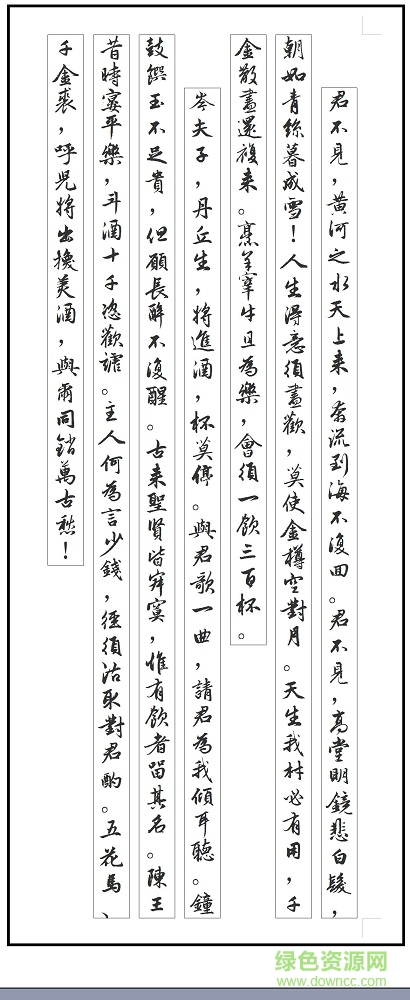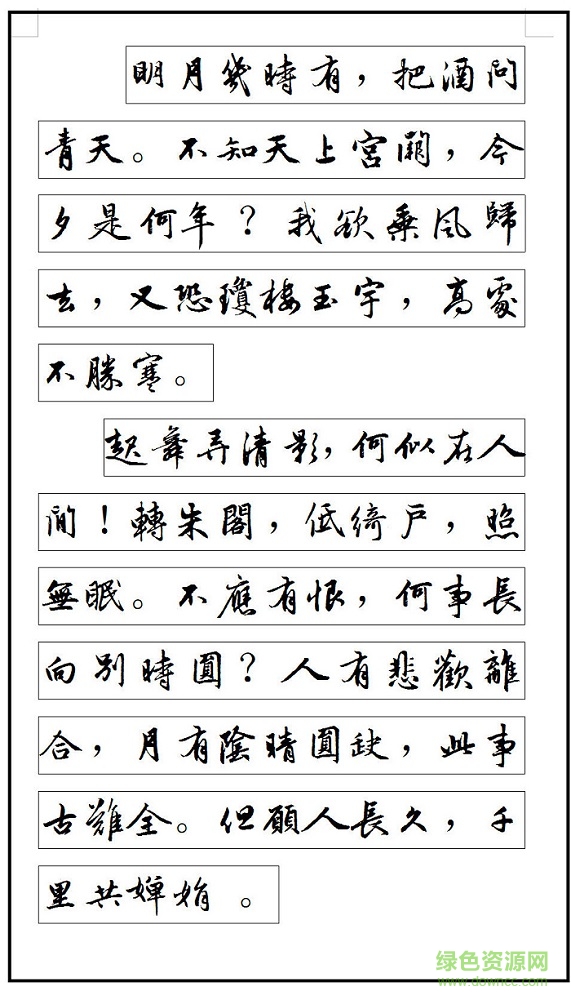
字酷堂南元松雪行書是字庫堂全新推出的一款行書字體,字體大氣磅礴、氣勢威嚴,不失行書的流暢灑脫,又有著獨特的娟秀端莊美,喜歡的朋友不妨來綠色資源網(wǎng)體驗吧!
字酷堂南元松雪行書,支持中文繁簡體,包含繁字字形七千余字,整體融合了行書靈活流動之氣,和獨特的大氣灑脫韻味。
南元松雪行書一說是趙孟頫趙體,因趙孟頫號松雪道人。
趙體楷書用筆沉穩(wěn),章法分明,外貌圓潤而筋骨內(nèi)涵,其點畫華滋遒勁,結體寬綽秀美,平中寓險,點畫之間呼應十分緊密。,趙體楷書既保留了唐楷的法度,又不拘泥于唐楷的一招一式,在楷書中經(jīng)常有一些生動俊俏的行書筆法與結構,筆劃形態(tài)生動自然,趙體楷書被譽之為活的楷書;而趙體行書溫潤閑雅,輕盈流動;筆法精致秀美充滿了書卷氣與富貴氣。其“書法以用筆為上,而結字亦須用工。蓋結字因時相傳,用筆千古不易?!币殉蔀榍Ч琶浴?/p>